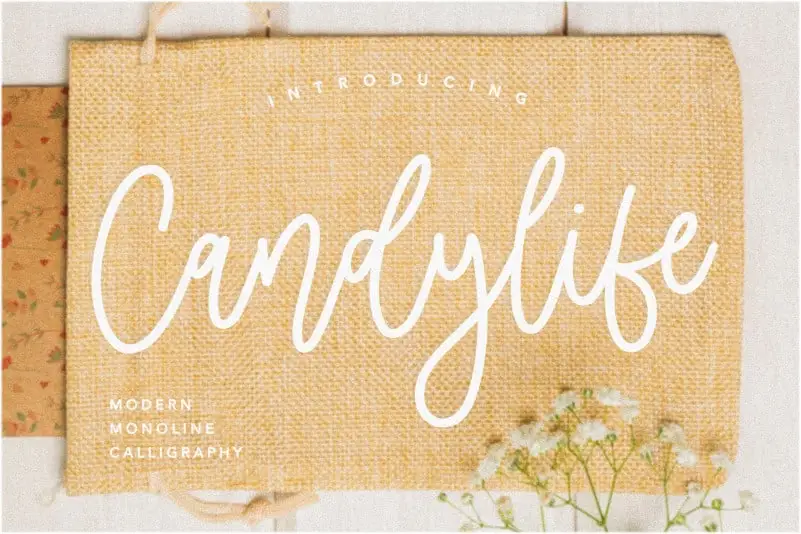
Candylife Monoline Calligraphy Font – Download Grátis
A Candylife Monoline Calligraphy Font é uma escolha perfeita para projetos que exigem um touch delicado e elegante. Seja para criações de embalagens de produtos, identidade visual ou até mesmo editoriais e redes sociais, a Candylife proporciona um toque refinado que brilha sob qualquer formato. Suas linhas leves e finas criam uma harmonia única que se torna o coração vibrante de cada projeto. Seja para destacar mensagens importantes em sites ou cartazes, ou simplesmente para expressar frases no topo de fundos suaves, a Candylife Monoline Calligraphy Font garante um resultado profissional e envolvente. Suas linhas contínuas proporcionam uma escrita fluida que se destaca com facilidade. Para quem busca algo delicado e sofisticado para seus projetos gráficos, a Candylife é uma fonte de primeira classe.